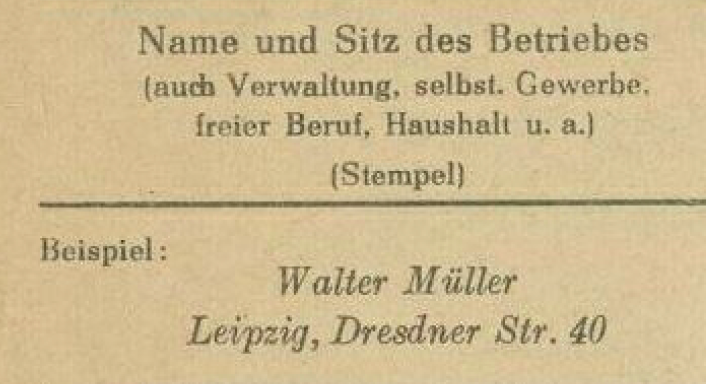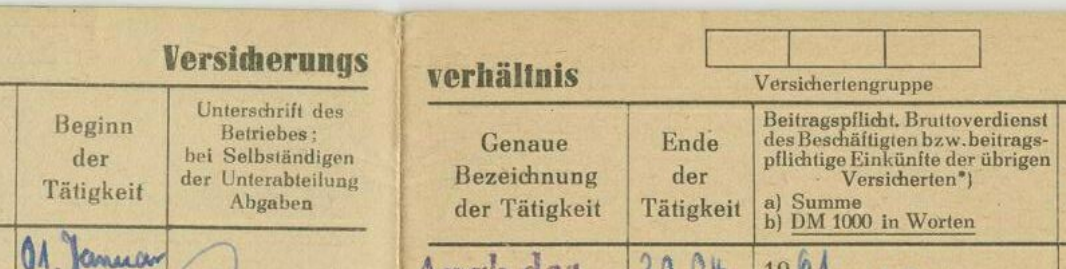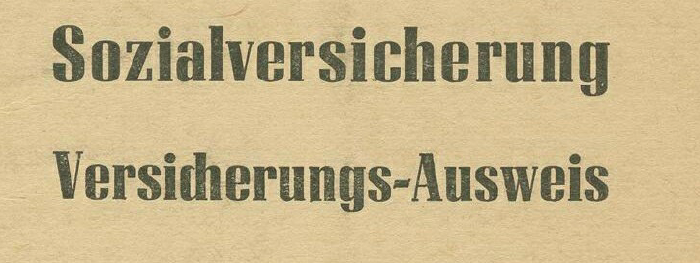
Schrift DDR-Sozialversicherungsausweis 60er Jahre
Für die Herstellung eines Faksimiles müsste ich wissen, welche Schrift für den DDR-Sozialversicherungsausweis verwendet wurde.
Corvinius und/oder Manutius - würde ich mal vermuten.
Danke, für den Titel könnte die Corvinius wirklich hinkommen. Aber die Schrift auf dem unteren Bildern muss eine andere sein. hat noch jemand eine Idee?
Was meinst du mit "ohne Artefakte"? Das sind alles Bilder des Originals. Ich möchte eine Kopie herstellen und dafür hätte ich eben gerne die entsprechende Schrift. Hier noch einmal ein anderes Bild. Ich wäre wirklich dankbar, wenn jemand die Schrift kennt. Hier gibt es doch einige DDR-Schrift-Experten.
Danke Ralf. Dann fehlt mir nur noch die kursive Schrift.
Die De Vinne Itlaic kommt der Kursiven wirklich sehr, sehr nah. Vielen Dank für eure Hilfe.